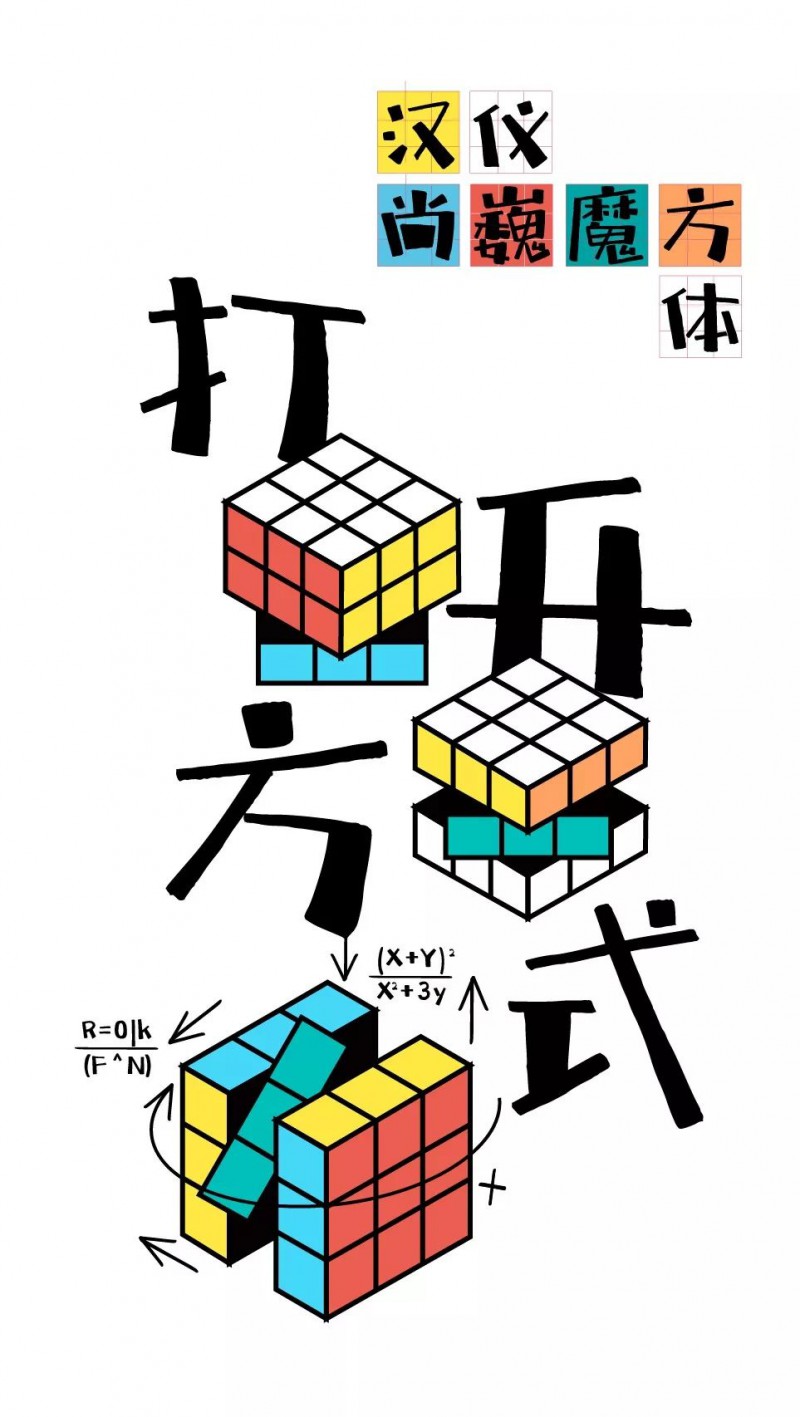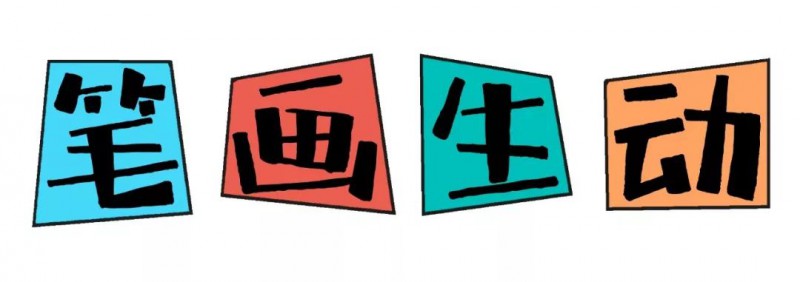
精选字体:生动的艺术一一汉仪尚巍魔方体
今天给大家介绍的这款字体是汉仪字库字体设计师尚巍的作品。该字体的名称是汉仪尚巍魔方体。尚巍一直都是字体设计师界非常优秀的人才之一,其还曾在电影《我不是药神》中的幕后花絮中写下了其最擅长的行书。
记得曾有这么一句话,比你优秀的人并不可怕,比你优秀的人还比你努力这是最可怕的。而尚巍便是这样的一个人,一个这么优秀的字体设计师依然对书法的学习继续探索,孜孜不倦。对于中国汉字的写法可能性,他从未停止过尝试。
尚巍的该款字体汉仪尚巍魔方体共由9169中文简繁 + 拉丁字符组成,改字最大的特点便是字形呈不规则四边形,灵动百变,笔画生动,变化自由。好了,话不多说带大家直接欣赏该字体。
这种魔方式写法的字体可以说让人看起来既惊奇又赞叹。该字单个笔画单独看,都是歪歪扭扭,杂乱丛生,但组合在一起,却又都是舒适而平衡的。
在这里不得不再次夸一波尚巍老师的字!!!真是既充满丰富想象力有好看。